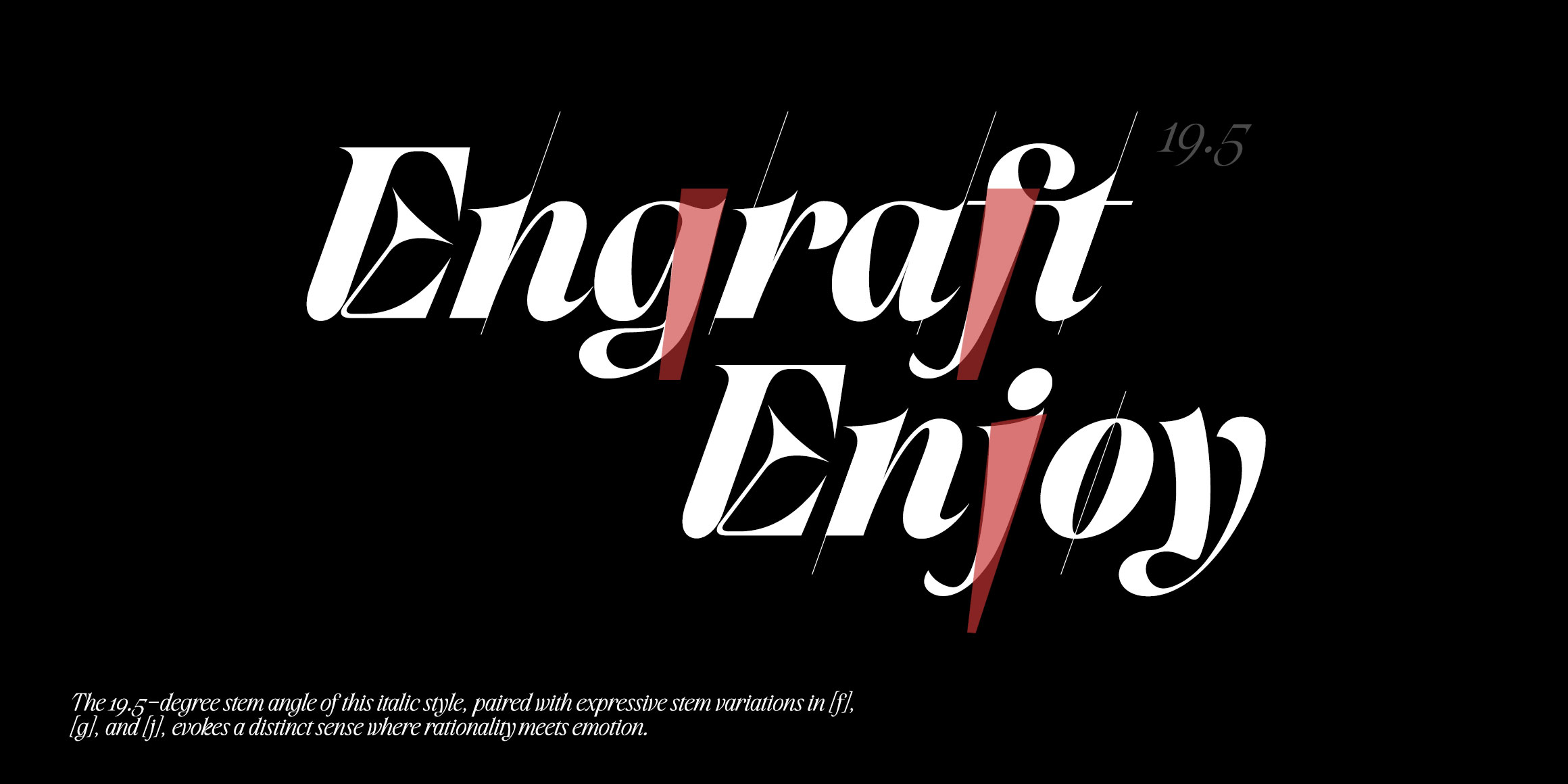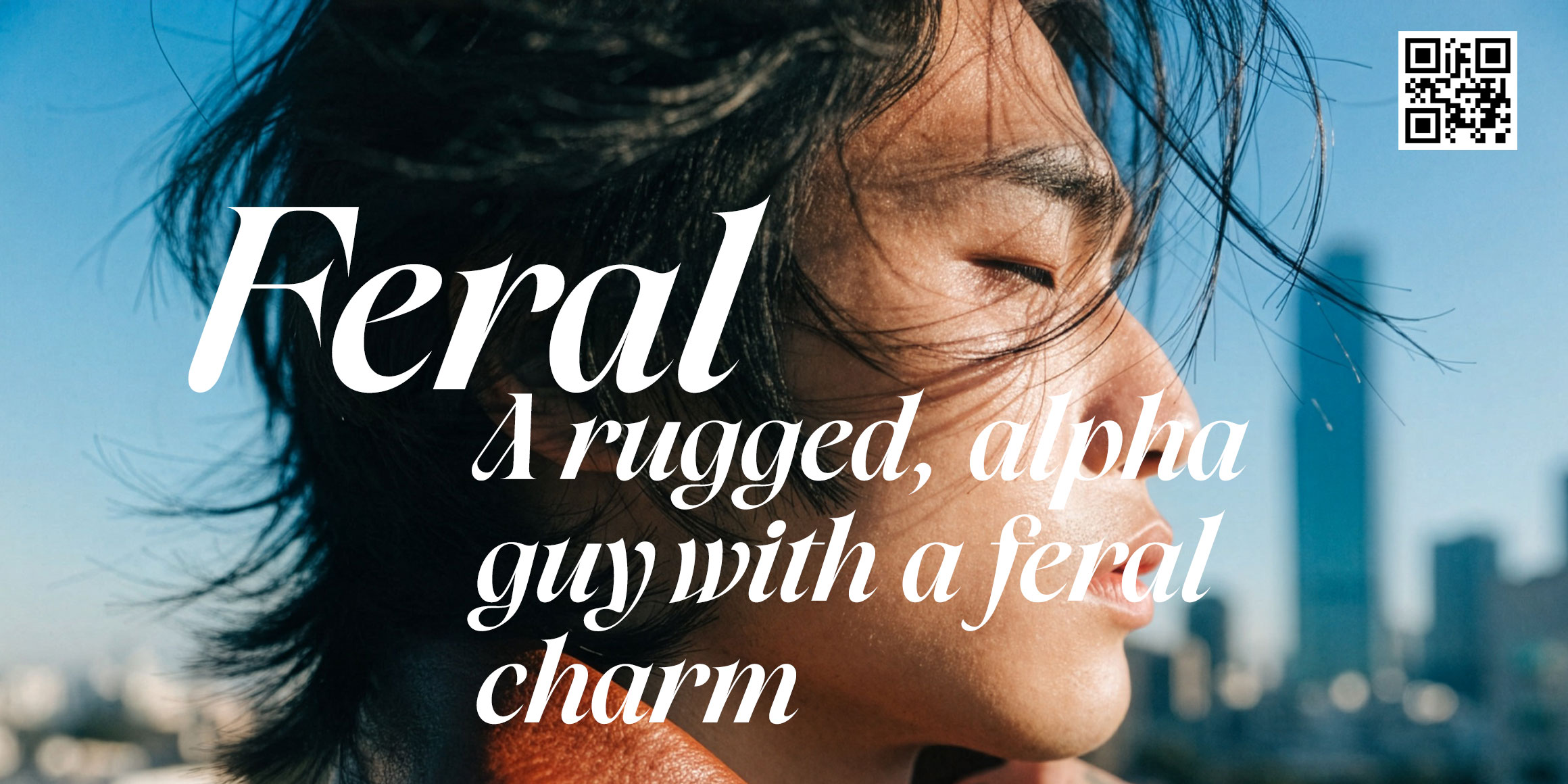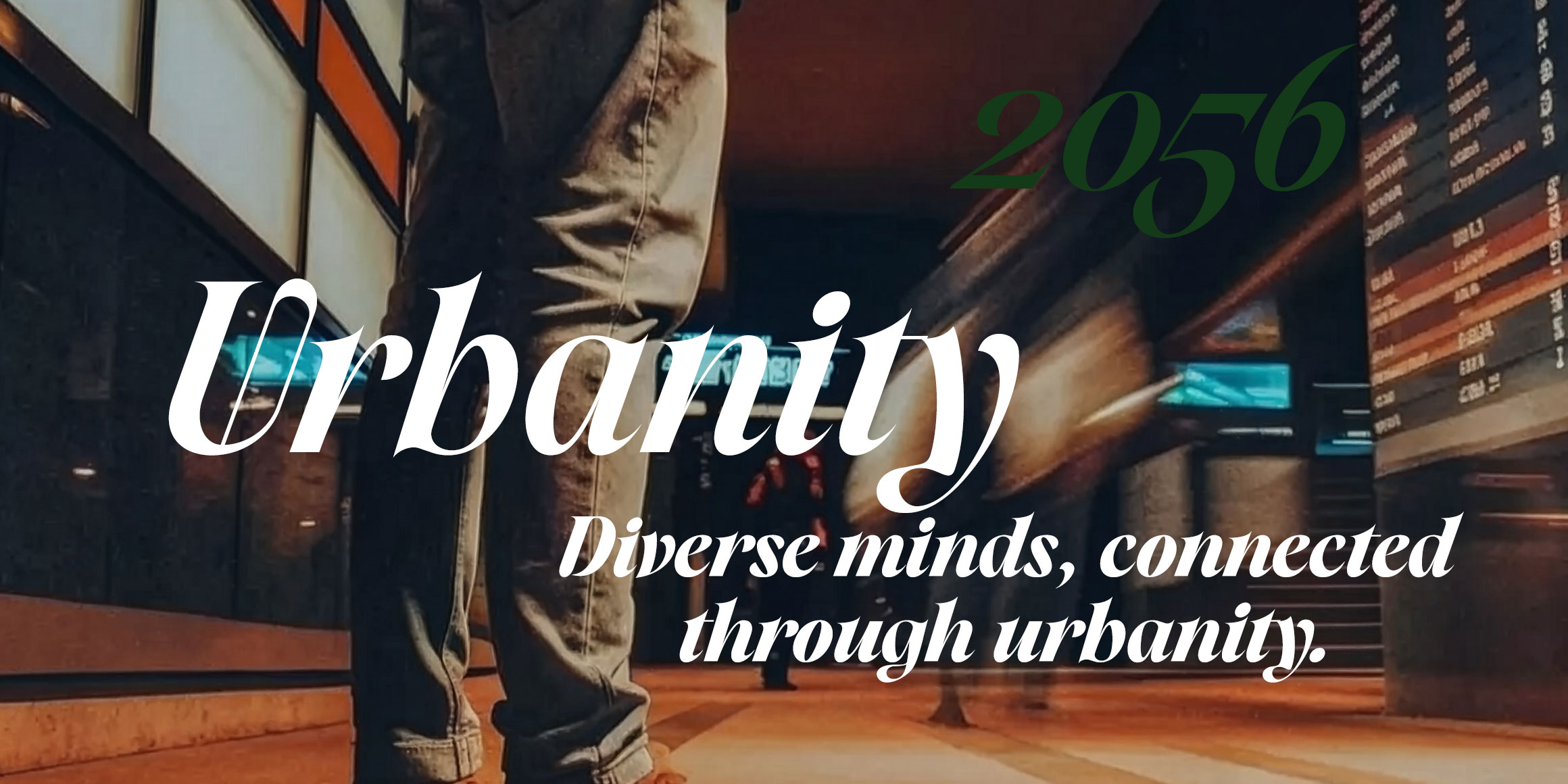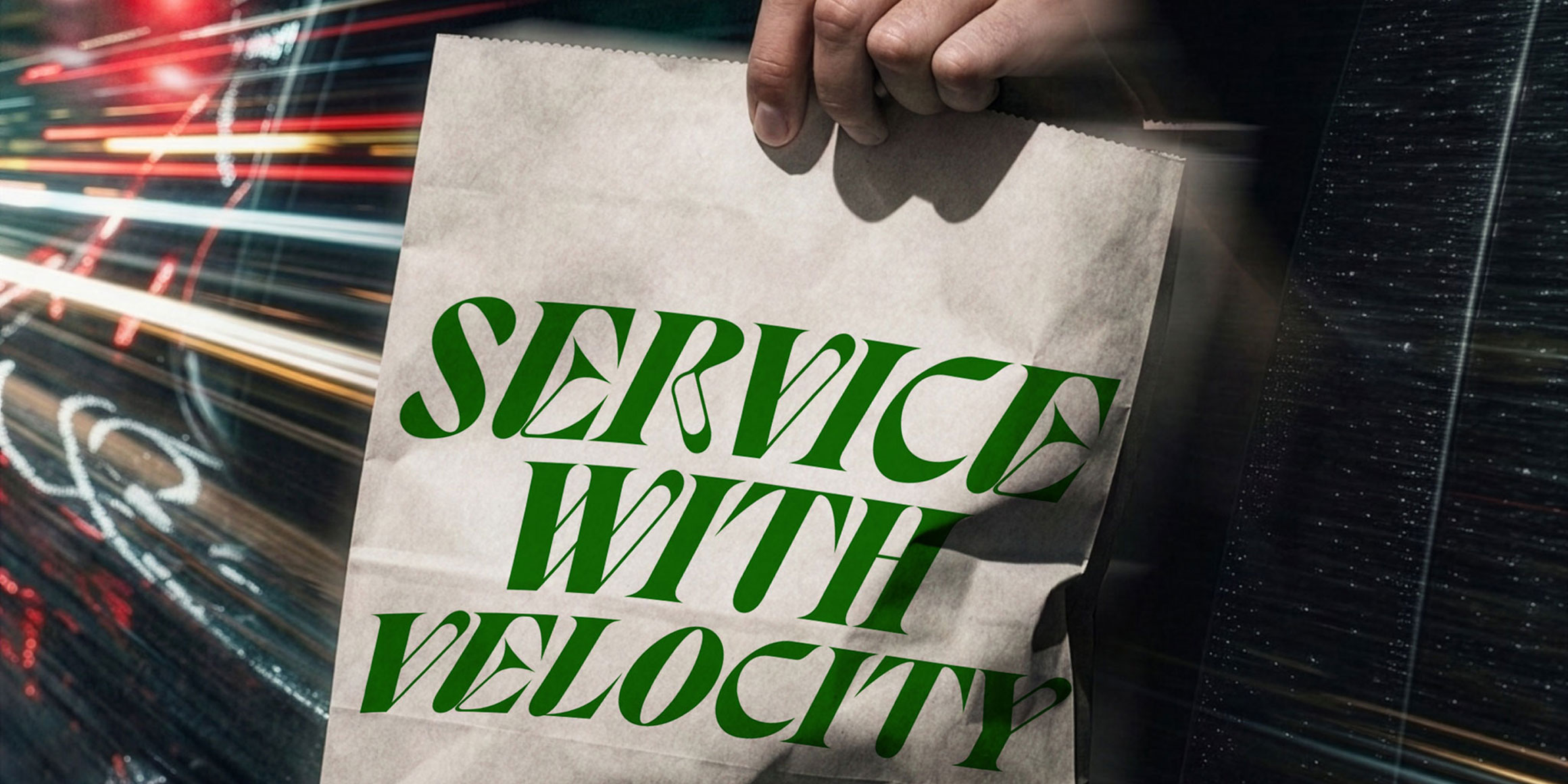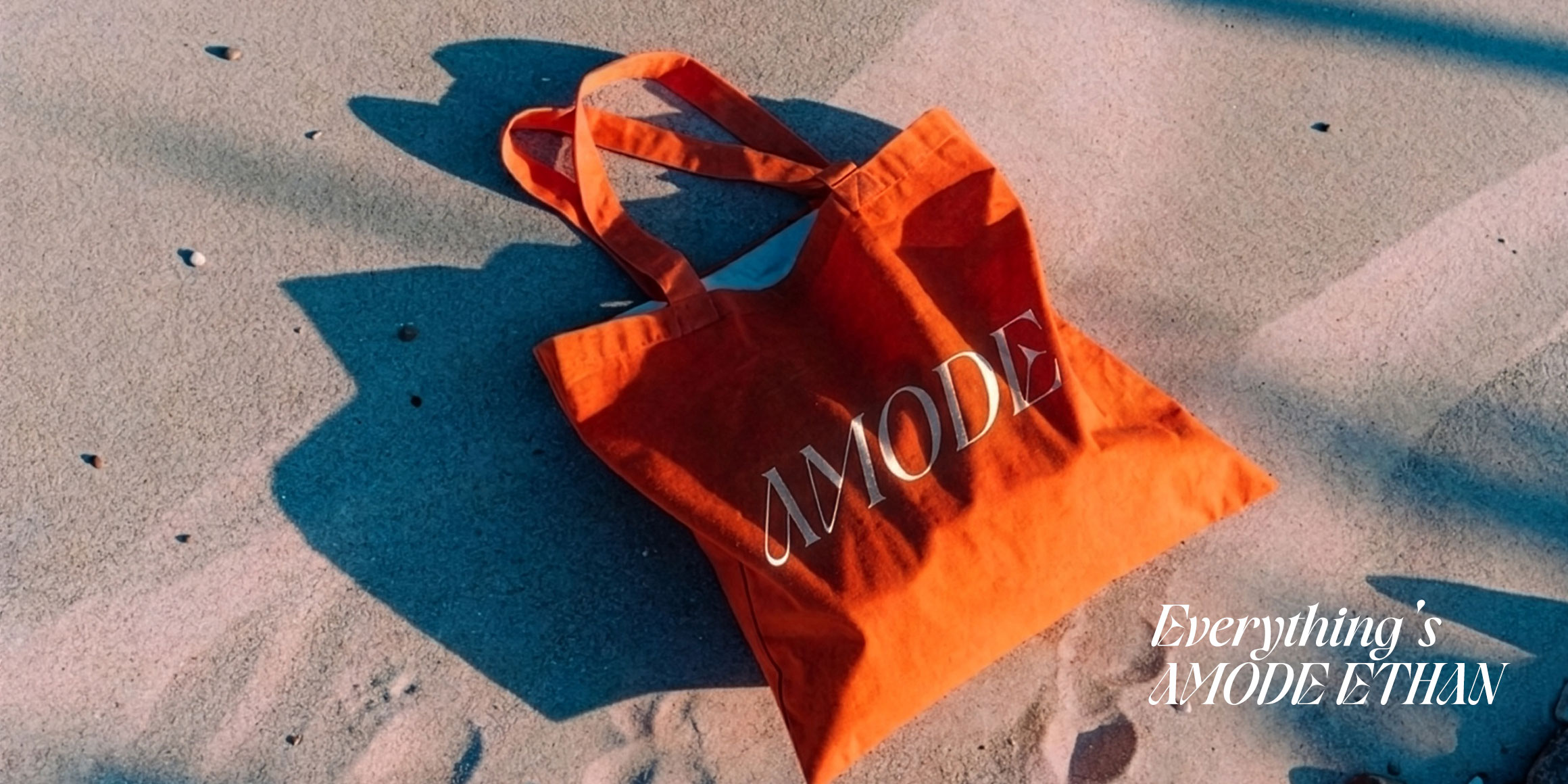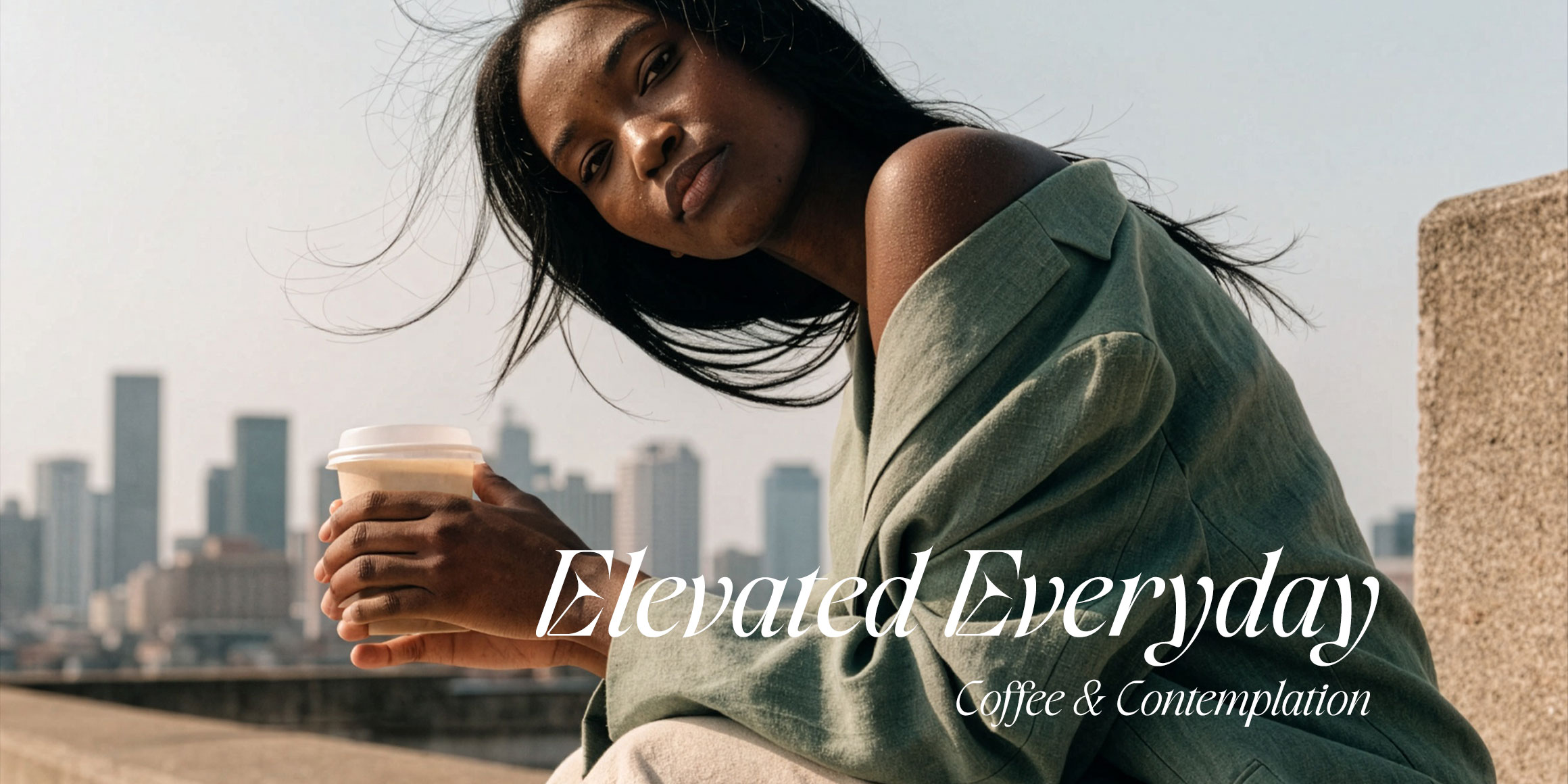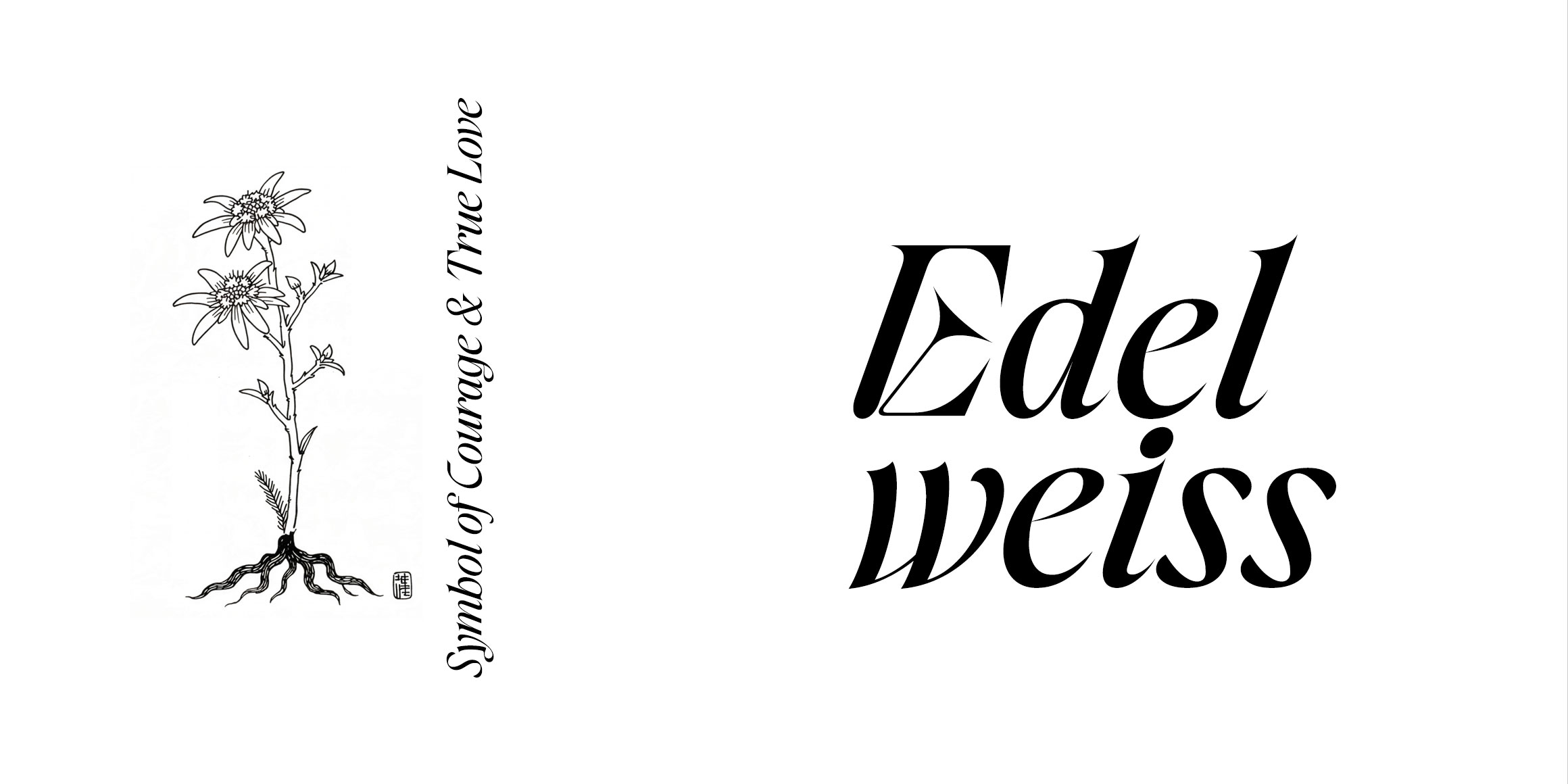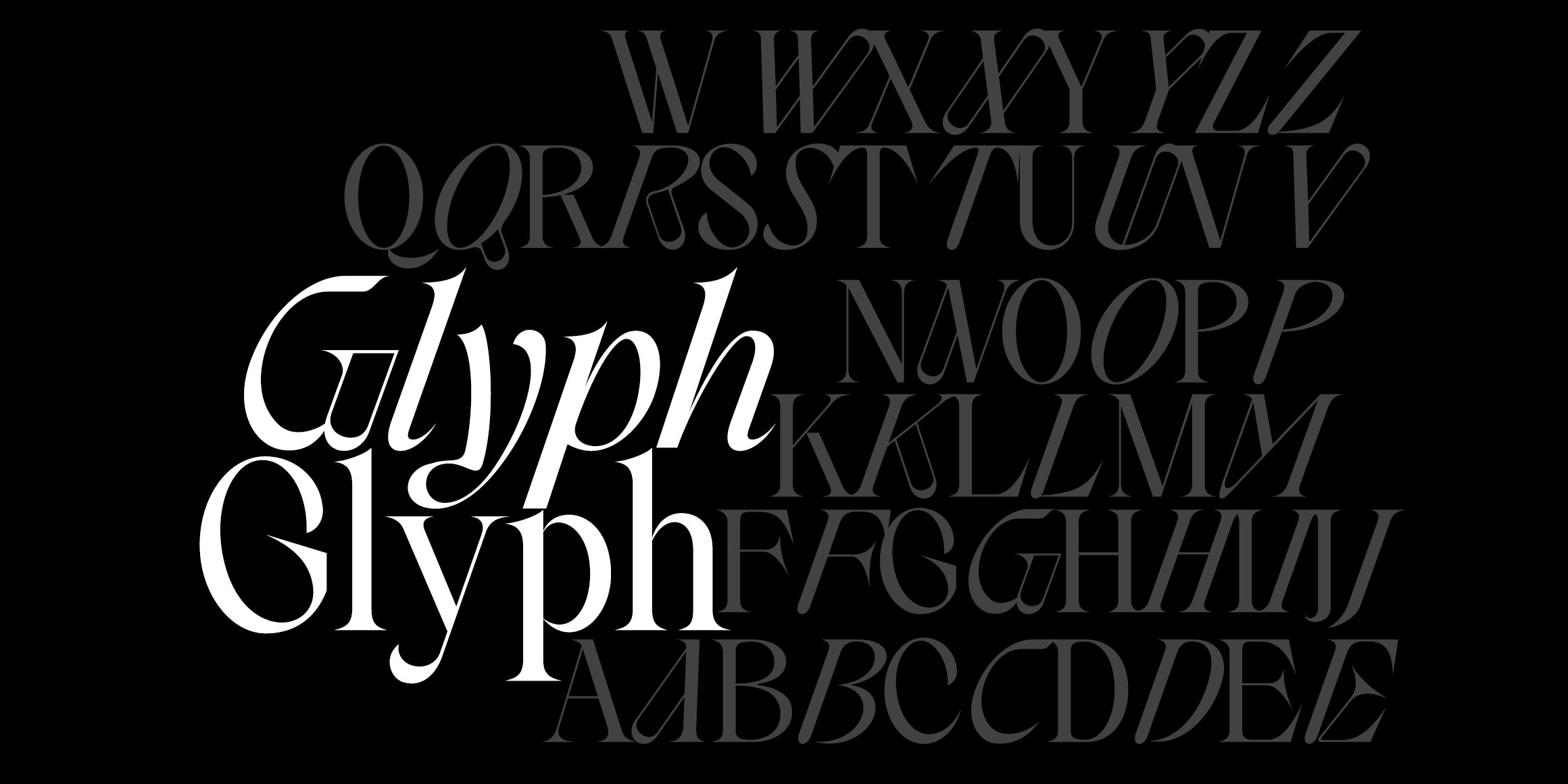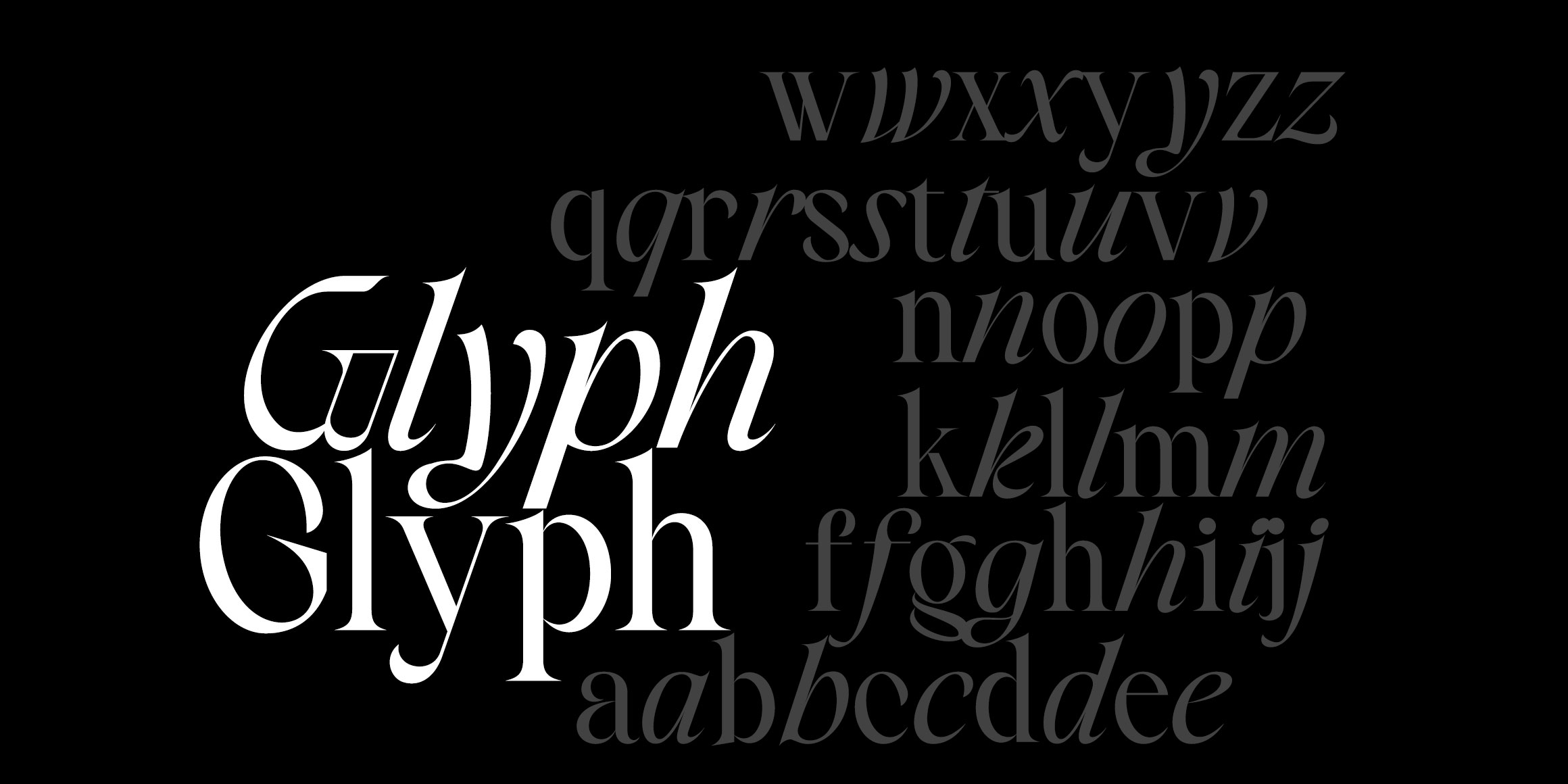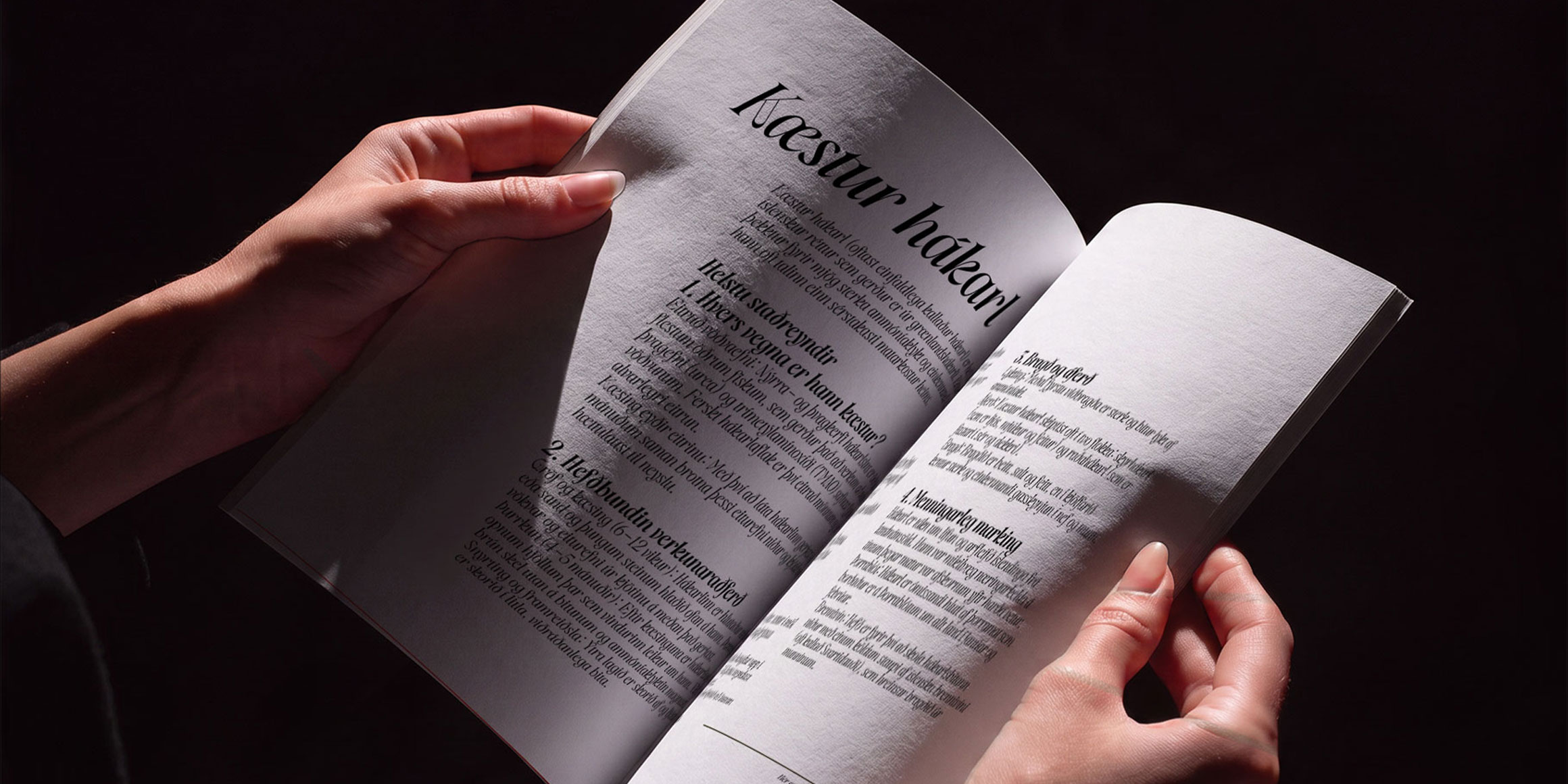
Amode Ethan
Amode Ethan은 모던 세리프(Serif)의 과감한 대비에 차갑고 지성적인 지오메트릭 디자인을 접목한 독특한 영문 전용 서체입니다.
특히 이탤릭(Italic) 스타일이 지닌 미학과 역동성에 집중하였으며, 19.5도의 다소 강한 기울기와 반항적 요소들이 상호 작용하는 독창적인 레이아웃을 포함합니다.
1. 시각적 분위기 및 디자인 의도 (Visual Mood & Aesthetic Intent)
-냉철한 지성 : 매우 날카로운 터미널(Terminals)과 자른 듯한 단면을 유지합니다. 인위적인 연마나 라운딩을 철저히 배제하여, 미래지향적이면서도 압도적인 차가움을 전달합니다.
-하이엔드 브랜드 지향성 : 과감하면서도 정제된 톤앤매너를 구현하여 럭셔리 테크, 편집 타이틀, 브랜딩 디자인에 차별적 존재감을 선사합니다.
2. 형태적·구조적 특징 (Anatomical Features)
-공학적 느낌의 스템(Stems) : 정밀 가공된 카라비나, 정교하게 컷팅된 단면, 또는 건축적 프레임을 연상시키는 접합부의 구조적 차별성을 지향합니다.
-압축된 에너지의 카운터(Counters): 글자 내부의 빈 공간(Counter)에는 전형적인 원형 포지션 대신, 의도적으로 변형된 곡선을 적용하여, 각 글자 안에 압축된 잠재 에너지를 시각화했습니다.